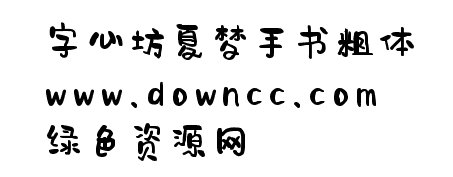
字心坊夏夢手書粗體是在原字體的基礎(chǔ)上進(jìn)行加粗設(shè)計的手寫字體,字跡有著十分活潑的造型和結(jié)構(gòu),給用戶的設(shè)計帶來很清新的藝術(shù)體驗,綠色資源網(wǎng)誠意推薦!
字體采用pop字體的書寫手法,用秀麗筆書寫,然后掃描后通過電腦設(shè)計軟件進(jìn)行去雜、修正、編輯、最后做成計算機(jī)字庫。字體風(fēng)格新穎、個性、小清新、時尚、有趣,適用于標(biāo)志、導(dǎo)視、書籍、游戲、動漫、影視、屏顯等方面。
該字體為字心坊夏夢手書字體系列作品的粗款字型字體。
字心坊夏夢手書粗體是一款清新時尚的藝術(shù)字體,主要用于藝術(shù)設(shè)計design,該字體風(fēng)格簡約、清新、時尚、手寫風(fēng)、有趣,且字體庫完整,可適用于創(chuàng)意設(shè)計字體、個性設(shè)計字體、海報設(shè)計字體、浪漫設(shè)計字體。